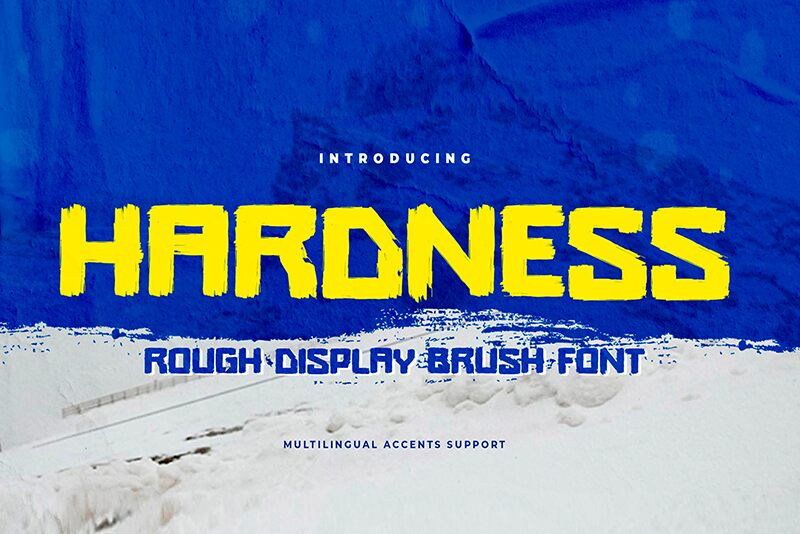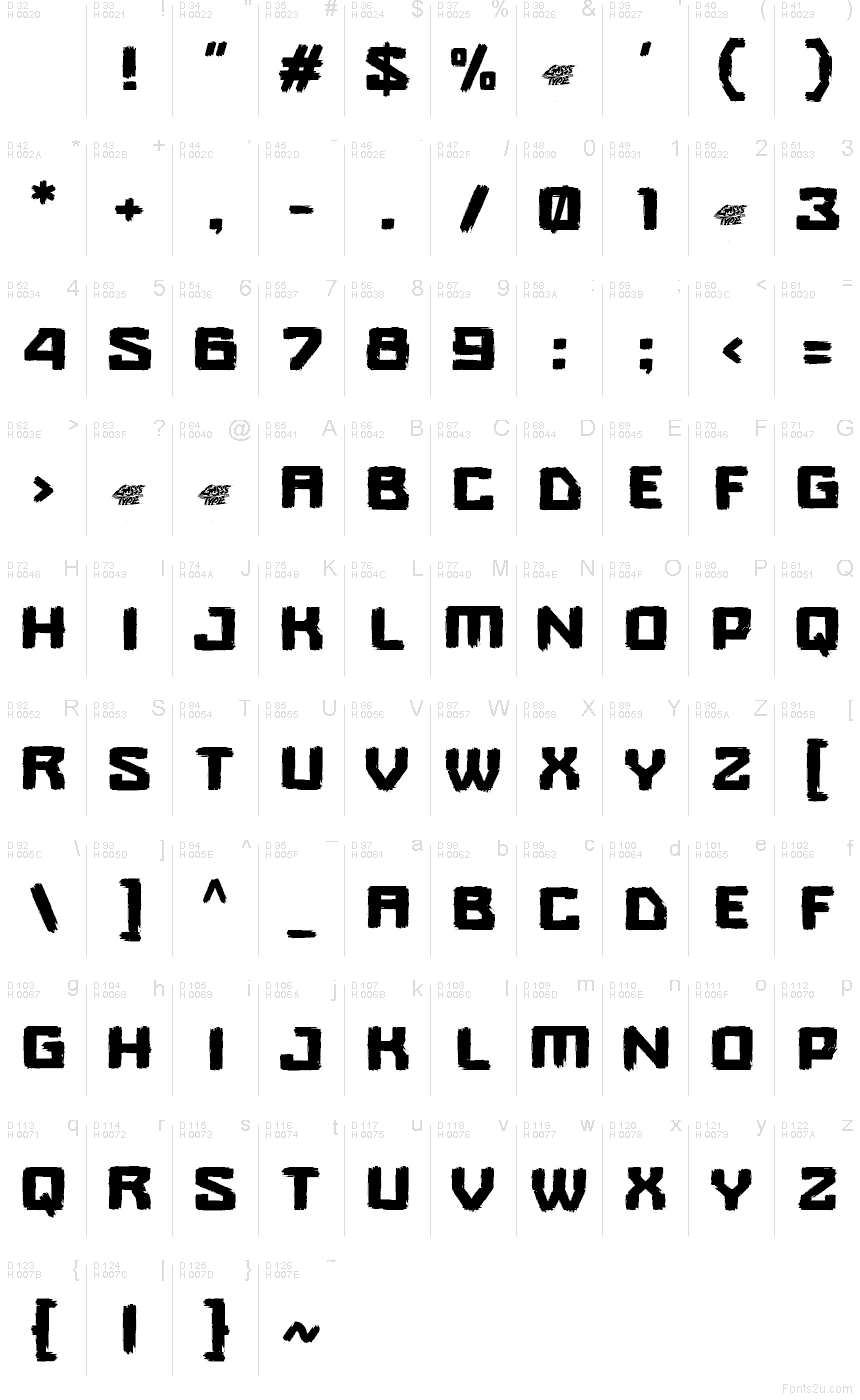
Hardness
Hardness di Gassstype Studio è un font gratuito in stile pennello ruvido, in maiuscolo, con un carattere diretto e quasi da poster. Le lettere sembrano tagliate con un pennello piatto, con striature verticali irregolari, angoli squadrati e bordi dentellati che mantengono un ritmo grezzo anziché troppo levigato.
Si adatta perfettamente a flyer musicali, branding streetwear, titoli di videogiochi, copertine di fanzine e packaging audaci dove un logotipo dal taglio rude riesce a trasmettere l'atmosfera da solo. Come font gratuito, Hardness funziona benissimo anche per titoli brevi, monogrammi e bozzetti di loghi, specialmente quando vuoi che le maiuscole sembrino potenti e fatte a mano, invece che troppo precise.